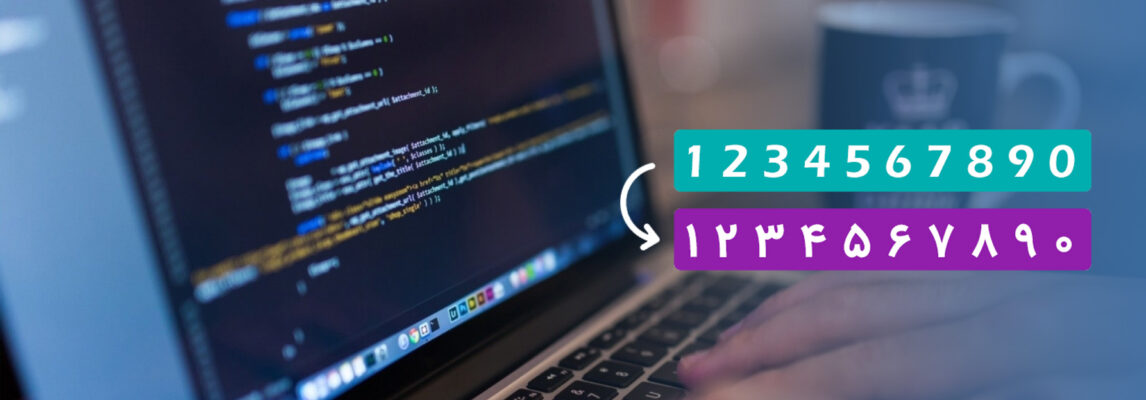
فارسی کردن اعداد انگلیسی در وب‌ سایت
مشکلات اعداد فارسی در وب
یکی از مشکلات رایجی که اخیرا برنامه نویس ها و طراحان با آن درگیر هستند. مشکل فارسی سازی اعداد در وبسایت ، اپلیکیشن و برنامه‌های حروفچینی و گرافیکی است.
در این مقاله قصد داریم توضیح دهیم مشکل تایپ اعداد چیست و چگونه می‌توان آن را حل کرد.
مشکل چیست؟
1. کیبوردهای پیش‌فرض ویندوز و دیگر سیستم عامل‌ها در محیط وب و موبایل اعداد را فارسی تایپ نمی‌کنند. بنا‌براین ممکن است همیشه در وب یا نرم افزار با مقدار زیادی عدد روبرو باشیم که از ابتدا انگلیسی تایپ شده‌اند. (مقدار زیادی از این نوشته‌ها توسط کاربران تولید شده است و ما کنترلی روی نحوه تایپ آنها نداریم مانند کامنت‌ها، تالارهای گفتگو و شبکه‌های اجتماعی)
2. برخی اعداد توسط برنامه و یا سرور به صورت انگلیسی تولید می‌شوند و کنترل آنها در دست ما نیست مثل ساعت، تاریخ و یا دفعات بازدید و …
3. رواج فونت‌های با اعداد تمام فارسی تشخیص انگلیسی یا فارسی بودن اعداد را با مشکل مواجه کرده است.
چرا بعضی فونت‌ها اعداد فارسی را فارسی نشان می دهند و بعضی انگلیسی؟!
مشکل از سال ها قبل شروع شد. زمانی که تایپ فارسی در محیط کامپیوتر اولین قدم های خودش را برمی‌داشت و کم کم حروفچینی کامپیوتری جایگزین روش های قدیمی چاپ شده بود.
در همان زمان بود که بعضی شرکت های ایرانی خواستند حروف تایپی موجود در صنعت نشر و چاپ ایران را به فونت تبدیل کنند و چون در آن زمان هم (خیلی جدی تر از الان) مشکل کیبورد فارسی وجود داشت. هنگام تایپ فارسی، عددها انگلیسی بودند و حتی بعضی حروف، عربی تایپ می‌شدند. این بود که راه حل جالبی به ذهنشان رسید!
راه حل این بود که در فونت های تولید شده، شکل گرافیکی اعداد انگلیسی را به شکل فارسی تغییر دهند.
(و البته چند تغییر دیگر مثلا به جای«ي» و «ك» عربی ، «ی» و «ک» فارسی قرار دادند.)
در ظاهر این هکِ ساده به خوبی کار می‌کند و موقع تایپ برای همیشه از دست اعداد انگلیسی و حروف عربی راحت خواهیم شد.
این راه حل برای فارسی نویسی در حوزه چاپ به خوبی عمل می کرد تا زمانی که فارسی نویسی در محیط وب و نرم افزار به صورت جدی مطرح شد.
اینجا بود که دوباره آن اعداد انگلیسی و حروف عربی مزاحم پیدایشان شد. آن هم مثلا وقتی که حروفچین روزنامه مطلبی را با فونت میترا یا نازنین تایپ کرده بود و حالا قرار بود این مطلب روی وب سایت نشریه با فونت تاهوما دیده بشود!
بنابراین ما در حین کار با فونت‌های فارسی رایج با دو دسته فونت مواجه هستیم:
۱- فونت‌های عادی که اعداد فارسی را فارسی و اعداد انگلیسی را انگلیسی نشان می‌دهند. (مثل Tahoma  و Arial)
۲- فونت های با اعداد تمام فارسی (هک شده) که کلا همه اعداد (چه فارسی و چه انگلیسی) را فارسی نشان می‌دهند. (مثل Byekan )
استفاده از فونت با اعداد تمام فارسی چه مشکلی‌هایی ایجاد می کند؟
۱- مشخص ترین مشکل فونت‌های با اعداد تمام فارسی (هک شده) این است که نمی‌توان با آن اعداد انگلیسی را تایپ کرد. مثلا مجبوریم بنویسیم: ۳DMAX
تایپ ایمیل یا آدرس سایتی که حاوی عدد باشد هم با این فونت ها خیلی بدشکل خواهد شد. مثلا:  www.۹۸ia.com
۲- هنگام جستجو در مطالب سایت یا نرم افزار مشکلاتی ایجاد خواهد شد.
۳- ممکن است در برخی محاسبات مشکل ایجاد شود.
۴- با عوض شدن احتمالی فونت در مرورگرهایی که فونت ما را پشتیبانی نمی‌کنند مشکلات نمایان خواهد شد.
کاربرد فونت‌های با اعداد تمام فارسی:
با وجود تمام مشکلاتی که برای اعداد تمام فارسی ذکر شد مجموعه فونت‌های فونت‌ایران (مانند ایران‌سنس ، ایران یکان ، ایران شارپ و …) حاوی فونت‌های با اعداد تمام فارسی هستند.
استفاده از فونت‌های با اعداد تمام فارسی اگر با آگاهی از چگونگی عملکرد باشد انتخاب اشتباهی نیست و در واقع ساده‌ترین روش برای فارسی کردن اعداد است اما لازم است به مشکلات احتمالی آن کاملا آگاه باشید.
راه حل‌‌های استاندارد فارسی کردن اعداد انگلیسی چیست؟
1- فارسی وارد کردن اعداد از ابتدا
بهترین راه حل این است که از فونت استاندارد استفاده کنیم و برای تایپ اعداد به فارسی از کیبورد استاندارد فارسی استفاده کنیم. در ویندوز ۸ و یا بالاتر این کیبورد، با نا Persian(Standard)Keyboard در لیست کیبوردهای ویندوز وجود دارد. همچنین می توانید از این آدرس آن را دانلود و نصب کنید.
۲- فارسی کردن اعداد انگلیسی با کدنویسی
اما اگر اعداد از اول فارسی ایجاد نشده باشد مجبوریم اعداد انگلیسی را با فارسی جایگزین کنیم برای اینکار چندین راه با مزایا و معایب مختلف وجود دارد:
1- با توابع زبان های سمت سرور نظیر PHP : اگر برنامه نویس باشید قطعا میدانید که می‌شود توسط برخی توابع ، عبارات مورد نظر را با عبارت دلخواه دیگر جایگزین کرد . شما میتوانید توسط این توابع مانند تابع str_replace در زبان php آرایه ای از اعداد 0 تا 10 انگلیسی را با آرایه‌ای از اعداد 0 تا 9 فارسی جایگزین کنید . البته این تنها یکی از روش هایی بود که مارا به هدفمان می‌رساند .
برای مثال اگه ما : عدد 256 را برای $English_Number وارد کنیم خروجی $Persian_Number به صورت ۲۵۶ خواهد بود :
فارسی کردن اعداد انگلیسی در وردپرس
اگر سایتتان وردپرسی است و از یکی از افزونه‌های ParsiDate یا wp-jalali استفاده می‌کنید. به راحتی می‌توانید از بخش تنظیمات افزونه اعدادِ مربوط به تاریخ، مطالب، بخش نظرات و جاهای دیگر وبسایت‌تان را فارسی کنید.
فارسی کردن اعداد انگلیسی در وردپرس
برای فارسی کردن باقی بخش ها هم می‌توانید مستندات افزونه را مشاهده کنید توابعی برای فارسی سازی باقی بخش‌ها وجود دارد.